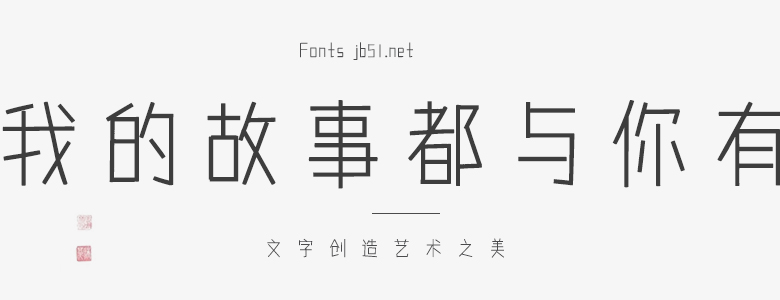
我的故事都與你有關(guān)該字屬工藝美術(shù)字,字體稍長(zhǎng),可彰顯字體挺拔俊秀之美。工筆鏤空,內(nèi)圓外方,有圓潤(rùn)穩(wěn)固之感。 采用橫細(xì)豎粗標(biāo)準(zhǔn),恪守隸法。追求美術(shù)字的創(chuàng)意規(guī)范,大小統(tǒng)一,字跡美觀。 創(chuàng)作中遵循,統(tǒng)一風(fēng)格,又不墨守成規(guī)。拓寬適用范圍,雅俗共賞,給人以美的享受。